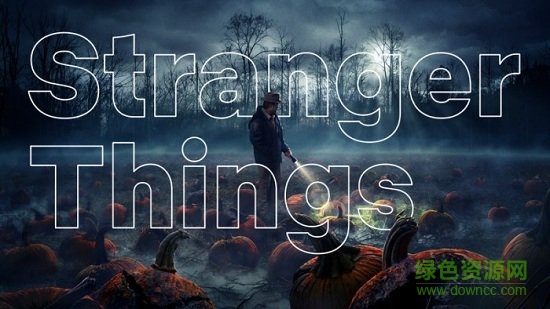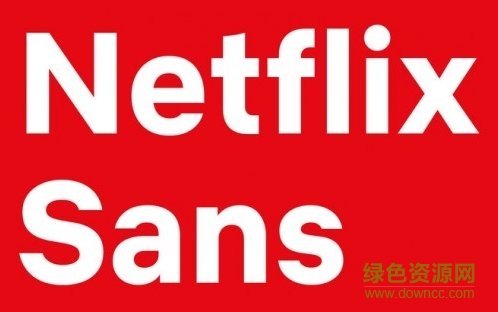
netflix sans是netflix官方推出的一款專屬字體,采用無無襯線的設(shè)計風(fēng)格,整體結(jié)構(gòu)十分大氣,字庫完整,較能滿足眾多設(shè)計要求,歡迎大家來綠色資源網(wǎng)搶先體驗!
Netflix Sans 由字體設(shè)計公司 Dalton Maag 與 Netflix 共同創(chuàng)造,采用了非常簡約的無襯線字體設(shè)計,Netflix將把新字體用于品牌推廣和市場宣傳中,讓Netflix擁有獨特的品牌識別度!
Netflix Sans 由字體設(shè)計公司 Dalton Maag 與 Netflix 共同創(chuàng)造,負責(zé)該項目的主管 Noah Nathan 表示,新字體不僅能幫公司省下使用 Gotham 字體帶來的每年「數(shù)百萬美元」版權(quán)費,同時也有助于提升 Netflix 獨特的品牌識別度。